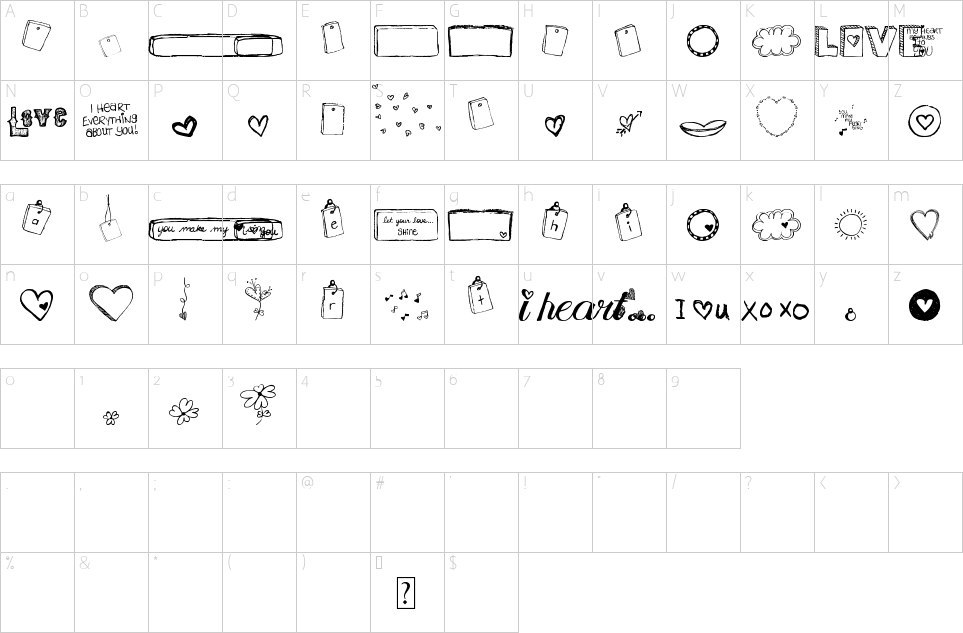
Descobri recentemente a fonte MTF I Heart Sketches, uma opção grátis e versátil para aqueles que desejam dar um toque delicado e artesanal em seus projetos digitais. Esta font foi criada pela designer Miss Tiina Fonts e disponibilizada de forma gratuita para que todos pudessem explorá-la. Com seu traço delicado e linhas finas, a MTF I Heart Sketches oferece um toque único que pode ser usado para criar designs únicos e originais. Recentemente, mais de 6.970 pessoas baixaram esta font para seu uso pessoal ou projetos de negócios, demonstrando sua relevância e popularidade. Se você está em busca de uma fonte que possa dar um toque especial a seus projetos, a MTF I Heart Sketches pode ser uma excelente escolha.